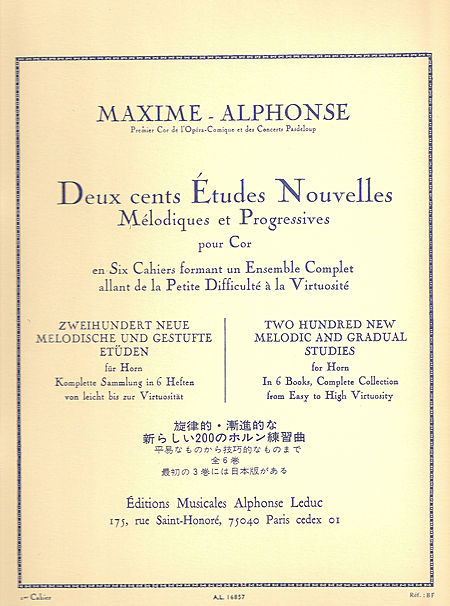
Umschlagentwurf für Noten
Ich will mich mal an einem neuen Umschlag für meinen Musikverlag versuchen. Hab ihr Tipps oder vielleicht ein Beispiel für einen besonders gelungenen Umschlag? In meinem Regal stehen hunderte von negativen Beispielen für Notenausgaben!
Bisher sieht es bei mir so aus
Das gesamte A3 Blatt ist ein Farbverlauf von Blau in Weiß, der Verlauf endet etwa bei 2/3 der Seite.
Nur leider gibt es in der Musikalienbranche keine Vorbilder. 90% = Titel + Komponist auf farbigen Papier siehe hier:
Und bei diesem Beispiel kann man schon von Typographie sprechen!!
Ich habe auf der Buchmesse den Stand dieses Verlages gesehen. Gähn!
das ist doch gar nicht so schlecht, sehr klassisch aber viele besser als das in deinem ersten post.
spricht dich das an?
Kennst du das reale Erscheinungsbild von Henle? Da stimmt vielleicht der typographische Satz der Schrift, die Farbe des Umschlags ist grausam.
Bei meinem Entwurf musste ich mit einfachen Mitteln einen universellen Umschlag machen. Da es damals auch auf einem Kopierer funktionieren sollte, durfte keine Farbe unter dem Text sein, der draufkopiert wurde. Und einen vernünftigen Verlauf hinzubekommen war schon ein Abenteuer. Also mit den Mitteln vor 11 Jahren!!
Ganz spontan: Alphonse Leduc hat im großen und ganzen eine recht schlichte, mich aber ansprechende Umschlaggestaltung.
Auf die Schnelle habe ich im Netz nur dies gefunden:
Das ist etwas gequetscht, weil so viel drauf steht. Vielleicht komme ich später dazu noch mal ein etwas hübscheres Beispiel zu photographieren. Aber das Prinzip wird klar.
Die schönsten Beispiele kommen für mich ja eigentlich nach wie vor von den alten Noten der alteingesessenen Verlage. Ausgaben von um 1900 stellen für mich den Inbegriff schöner Noten dar. Das ist zwar ziemlich üppig, aber damit bin ich halt groß geworden. Spätestens seit dem Computerzeitalter herrscht da Wildwuchs. Ist eigentlich auch klar: Der Umschlag ist zunächst mal völlig sekundär; ich habe noch nie Noten wegen des Umschlages gekauft. Die Gestaltung nimmt man als Musiker hin. Warum sollten die Verlage da also stark investieren?
Übrigens, so als technische Randbemerkung: Immer mehr Verlage gehen dazu über einen vollfarbigen Umschlag zu drucken. So im Stile von Heinrichs erstem Beispiel. Davon kann ich nur dringend abraten. Noten werden in der Notenmappe oder im Rücksack dauerhaft durch die Gegend getragen. Die vollfarbigen Umschläge reiben fast alle ab und man bekommt die Farben auf andere Noten. Ich kann das auf den Tod nicht ausstehen, das ist eine riesige Sauerei. Schon deshalb sind die AL-Noten recht gut, das ist einfach schön gefärbter Karton. Die färben nix ein! :x
Viel Information, gefällt mir aber überhaupt nicht
Das ist eben das nächste Problem: Noten sind als Druckerzeugnisse ziemlich international. Entweder man liefert alle Informationen in jeder Ausgabe, wie Alphonse Leduc es macht, oder man hat eine schlichtere Gestaltung, muß dann aber für Englisch, Französisch etc. eigene Ausgaben bereitstellen. Nur wenn im Grunde keine geschriebene Information vorliegt wird darauf keine Rücksicht genommen. Orchesterliteratur wird idR nur in einer Sprache herausgegeben; sehr zur Qual der Orchestermusiker hier wenn es um Bruckner oder Mahler geht und Dinge wie »Schalltrichter in die Höhe« oder »im Tempo eines ländlichen Walzers« auftauchen.
Wenn man das ganze reduktionistischer macht, dann landet man im Grunde bei einem ähnlichen Erscheindungsbild, nur mit weniger Information (Boosey & Hawkes).
Diese »Konsistenz« in der Gestaltung (Edition Peters, Bärenreiter, Schott etc.) zeigt dabei, daß eine aktive Gestaltung nur bedingt von Interesse ist; formal interessiert es die Musiker, also die Zielgruppe eben kaum. Man kann natürlich eine speziellere Gestaltung machen (dieses Beispiel gefällt mir ganz gut), aber das ist dann nur für die Flötenausgaben nützlich. Das macht bei größen Verlagshäusern einfach zu viel Arbeit.
Ich meinte übrigens sowas hier – ziemlich überladen aber für mich der Inbegriff schöner Noten! :wink: